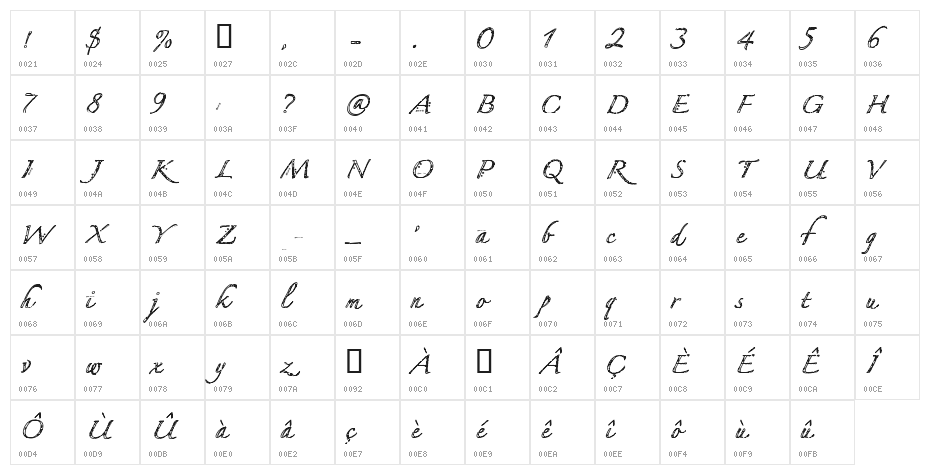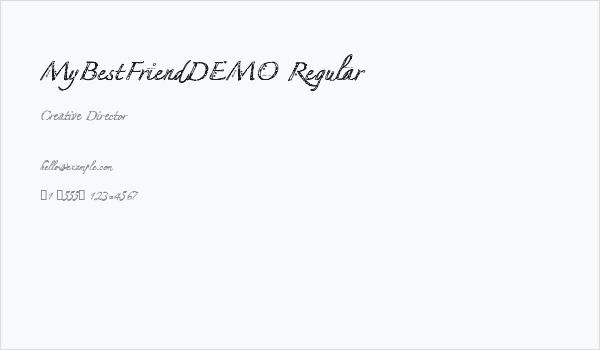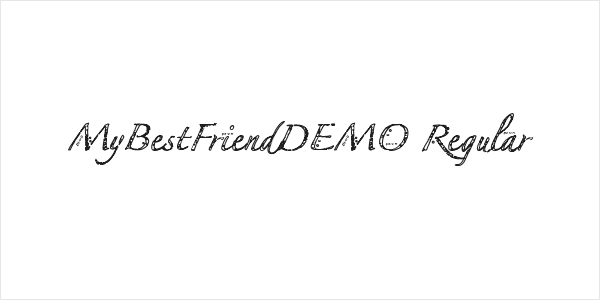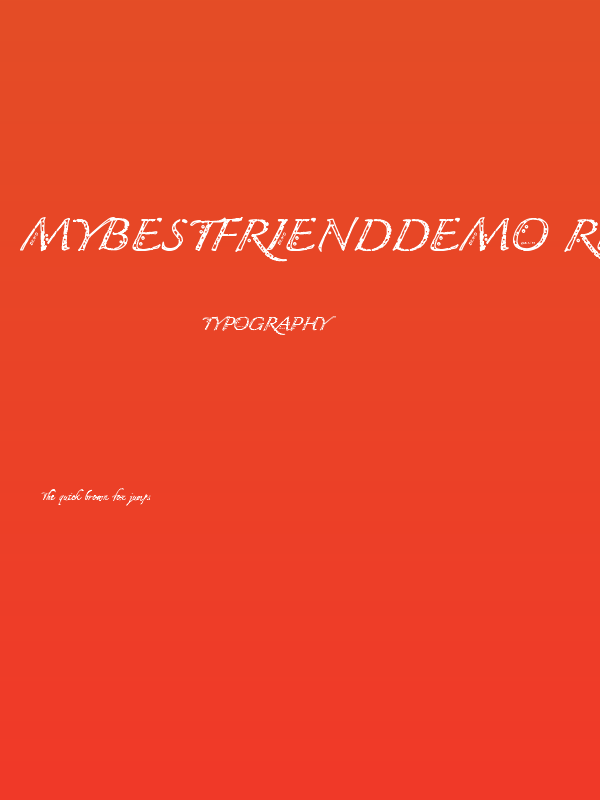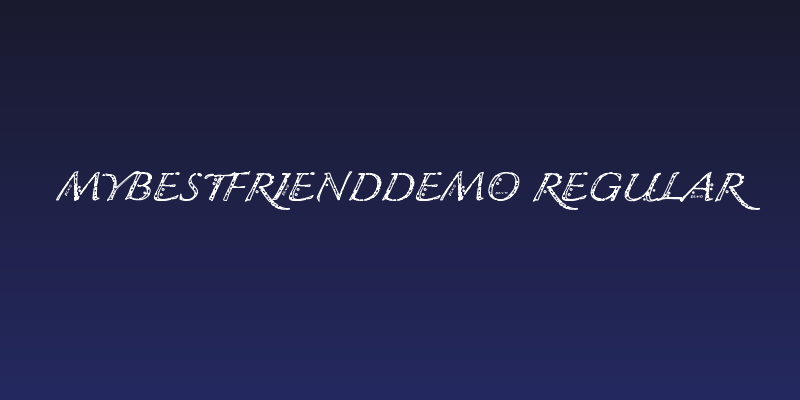
MyBestFriendDEMO Regular Font
| Caso de uso | Logos, Headlines, Artistic projects |
| Proyectos propuestos | Ideal for greeting cards, invitations, artistic posters, and branding materials that require a personal and creative touch. |